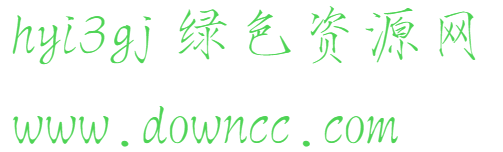
hyi3gj字體又叫漢儀瘦金書字體,該字體筆畫瘦勁,線條靈動,頗顯風骨,可用于文藝設計、古代影視設計等領域,需要的朋友快來綠色資源網(wǎng)下載吧!
瘦金體是宋徽宗趙佶所創(chuàng)的一種字體,是書法史上極具個性的一種書體,因其與晉楷唐楷等傳統(tǒng)書體區(qū)別較大,個性極為強烈,故可稱作是書法史上的一個獨創(chuàng),因其筆畫相對瘦硬,故筆法外露,可明顯見到運轉提頓等運筆痕跡,是一種風格相當獨特的字體。